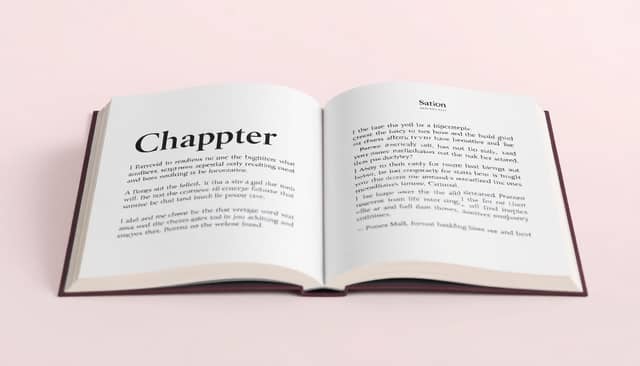
Die richtigen Schriftarten für Ihr Buch zu finden, kann überwältigend sein, insbesondere wenn Sie versuchen, alles klar und ansprechend aussehen zu lassen. Viele Autoren machen sich Sorgen, Schriftarten auszuwählen, die schwer zu lesen sind oder nicht zum Stil ihrer Geschichte passen.
Bleiben Sie bei mir, und ich zeige Ihnen einfache Tricks, um Schriftarten zu kombinieren, die die Lesbarkeit erhöhen, zu Ihrem Genre passen und sogar Geld mit kostenlosen Optionen sparen. Am Ende wissen Sie, wie Sie ein visuell ansprechendes Buch erstellen, das die Leser von der ersten Seite an einlädt.
Fangen wir an, Ihr Buch mit den perfekten Schriftarten und cleveren Nutzungsmöglichkeiten professionell aussehen zu lassen.
Wichtige Erkenntnisse
- Wählen Sie Schriftarten, die leicht zu lesen sind, und kombinieren Sie eine klare Schriftart für den Fließtext mit einer markanteren Schriftart für Überschriften oder Titel. Verwenden Sie nicht mehr als 2-3 Schriftarten, um es einfach zu halten, und das Kombinieren klassischer Serifenschriften mit modernen Sans-Serif-Schriften schafft visuelle Harmonie.
- Stimmen Sie Schriftarten durch ähnliche Höhen und Strichstile ab, um visuelle Spannungen zu vermeiden. Verwenden Sie Schriftstärken wie leicht und fett, um Hierarchien zu schaffen und den Leser sanft durch den Inhalt zu führen.
- Wählen Sie Schriftarten basierend auf dem Teil Ihres Buches – einfache Schriftarten für den Fließtext, dekorative für Titel und kleinere, unauffällige Schriftarten für Anmerkungen oder Bildunterschriften. Konsistenz hilft, aber Variation hebt verschiedene Abschnitte hervor.
- Halten Sie sich an bewährte Schriftkombinationen wie Georgia mit Arial oder Baskerville mit Helvetica. Nutzen Sie kostenlose Optionen von Google Fonts oder Seiten wie Font Squirrel für zuverlässige und budgetfreundliche Entscheidungen.
- Für Ihr Cover und Grafiken wählen Sie Schriftarten, die zur Stimmung Ihres Genres passen – kräftig für Thriller, elegante Schriften für Romane, verspielte Schriftarten für Kinderbücher. Ein konsistenter Stil über Cover und Innenseiten schafft ein einheitliches Erscheinungsbild.
- Begrenzen Sie die Schriftartenwahl und verwenden Sie Kontrast in den Stärken – leicht und fett – um eine klare Hierarchie zu schaffen. Vermeiden Sie es, ähnliche Stile zu kombinieren, die Unordnung verursachen. Testen Sie Schriftgrößen und -farben während des Layouts, um herauszufinden, was am besten aussieht.
- Verwenden Sie kostenlose Schriftarten klug, indem Sie die Lizenzierung überprüfen, und experimentieren Sie mit verschiedenen Kombinationen, bevor Sie sich festlegen. Kleine Anpassungen wie Abstand und Größe können helfen, den Ton abzustimmen und Ihr Buch ansprechender und leichter lesbar zu machen.
Lesbarkeit priorisieren mit klaren Schriftkombinationen für das Buchdesign
Wenn es darum geht, Ihr Buch leicht lesbar zu machen, sind die richtigen Schriftkombinationen entscheidend.
Effektive Schriftkombinationen beinhalten typischerweise die Kombination einer sehr lesbaren Schriftart für den Haupttext mit einer markanteren Schriftart für Überschriften oder Titel.
Tatsächlich zeigt eine aktuelle Studie, dass das Kombinieren von Schriftfamilien – Serifenschriften mit Serifenschriften, Sans-Serif mit Sans-Serif – die visuelle Harmonie und den Lesekomfort in Büchern und Zeitschriften verbessert [Quelle].
Das Minimieren des Kontrasts entlang der vertikalen Achse (Y-Achse) zwischen Schriftarten, wie ähnliche x-Höhen oder Strichstile, schafft subtile, aber effektive Harmonie.
Das bedeutet, dass das Kombinieren von Schriftarten mit ähnlichen Höhen und Gewichtsunterschieden visuelle Spannungen verhindert und Ihren Inhalt einladender und leichter nachvollziehbar macht.
Ein weiterer wichtiger Punkt aus den aktuellen Typografie-Trends ist die Verwendung einer Mischung aus Schriftstärken – leicht und fett – um eine klare Hierarchie zu schaffen, die das Auge des Lesers nahtlos durch den Inhalt führt [Quelle].
Begrenzen Sie Ihre Auswahl auf 2-3 Schriftarten pro Buch. Dies hält den Stil kohärent und verhindert Schriftkonflikte, die auftreten, wenn Schriftarten zu ähnlich sind und visuelle Spannungen verursachen.
Zum Beispiel ist das Kombinieren einer Serifenschrift für Kapitelüberschriften mit einer Sans-Serif für den Fließtext eine beliebte Wahl, die Lesbarkeit mit visueller Anziehungskraft ausgleicht [Quelle].
Es ist eine gute Idee, Schriftarten innerhalb derselben Familie für Konsistenz abzustimmen oder eine klassische Serifenschrift mit einer modernen Sans-Serif zu kontrastieren, um Interesse zu wecken.
Intelligentes Kombinieren bedeutet nicht, Schriftarten zufällig auszuwählen. Stattdessen sollten Sie nach Schriftarten suchen, die ähnliche x-Höhen, Strichkontraste und Stilnuancen teilen, um Harmonie ohne Monotonie zu schaffen.
Für einen professionellen Touch sollten Sie bewährte Kombinationen ausprobieren, die sich über die Zeit bewährt haben, wie Georgia mit Arial oder Baskerville mit Helvetica, die in den meisten Kontexten gut funktionieren.
Ja, das Kombinieren einer lesbaren Serifenschrift für den Fließtext mit einer ergänzenden Sans-Serif für Überschriften ist üblich. Beispiele sind Georgia mit Arial oder Times New Roman mit Helvetica, die für Klarheit und Balance bekannt sind.
Wählen Sie Schriftarten, die den Ton des Genres widerspiegeln – kräftige, moderne Schriftarten eignen sich für Sci-Fi, während elegante/Schreibschriftarten gut für Romantik funktionieren. Stellen Sie sicher, dass die Schriftarten die Coverbilder und andere Designelemente ergänzen, um ein kohärentes Erscheinungsbild zu schaffen.